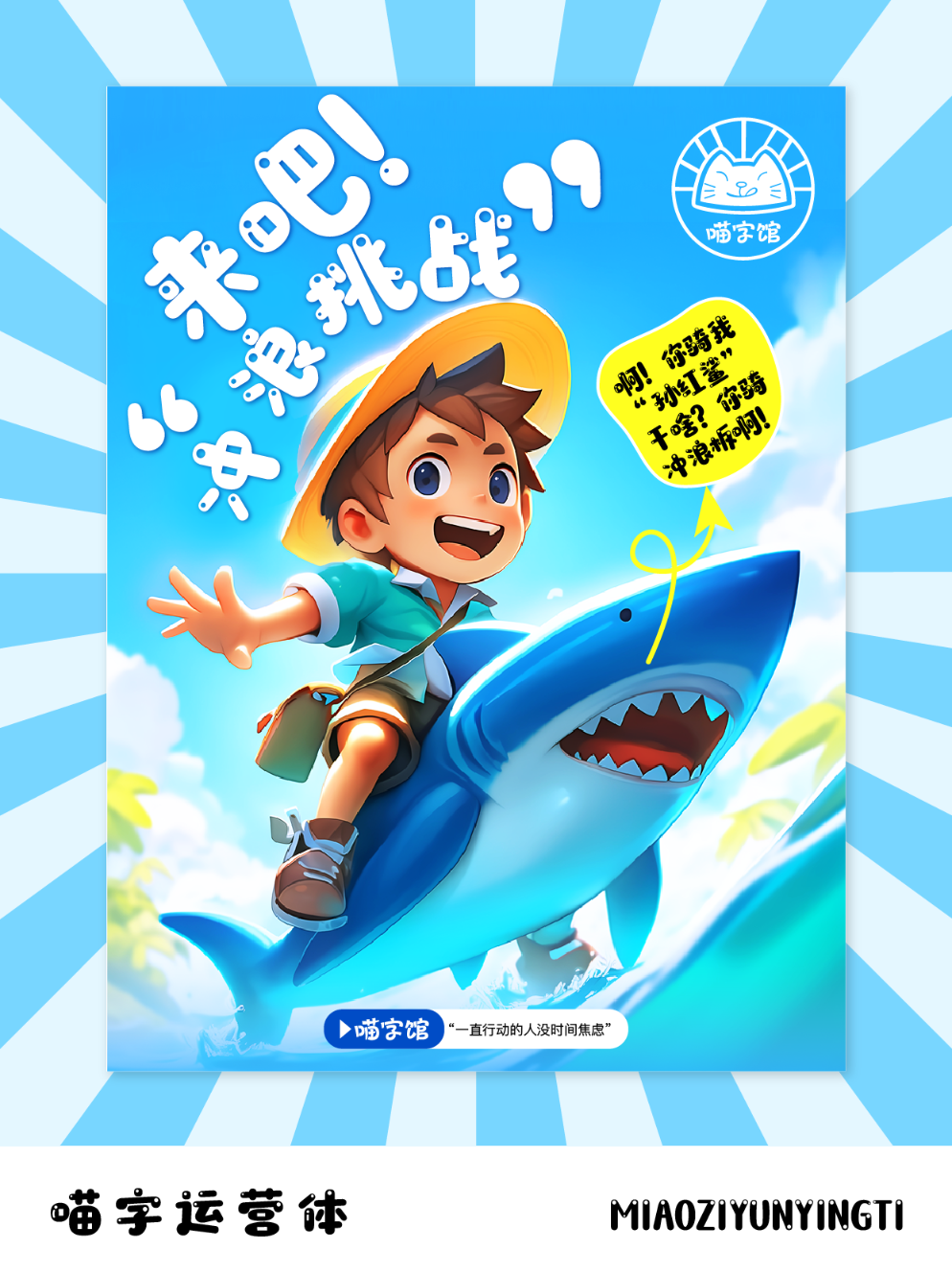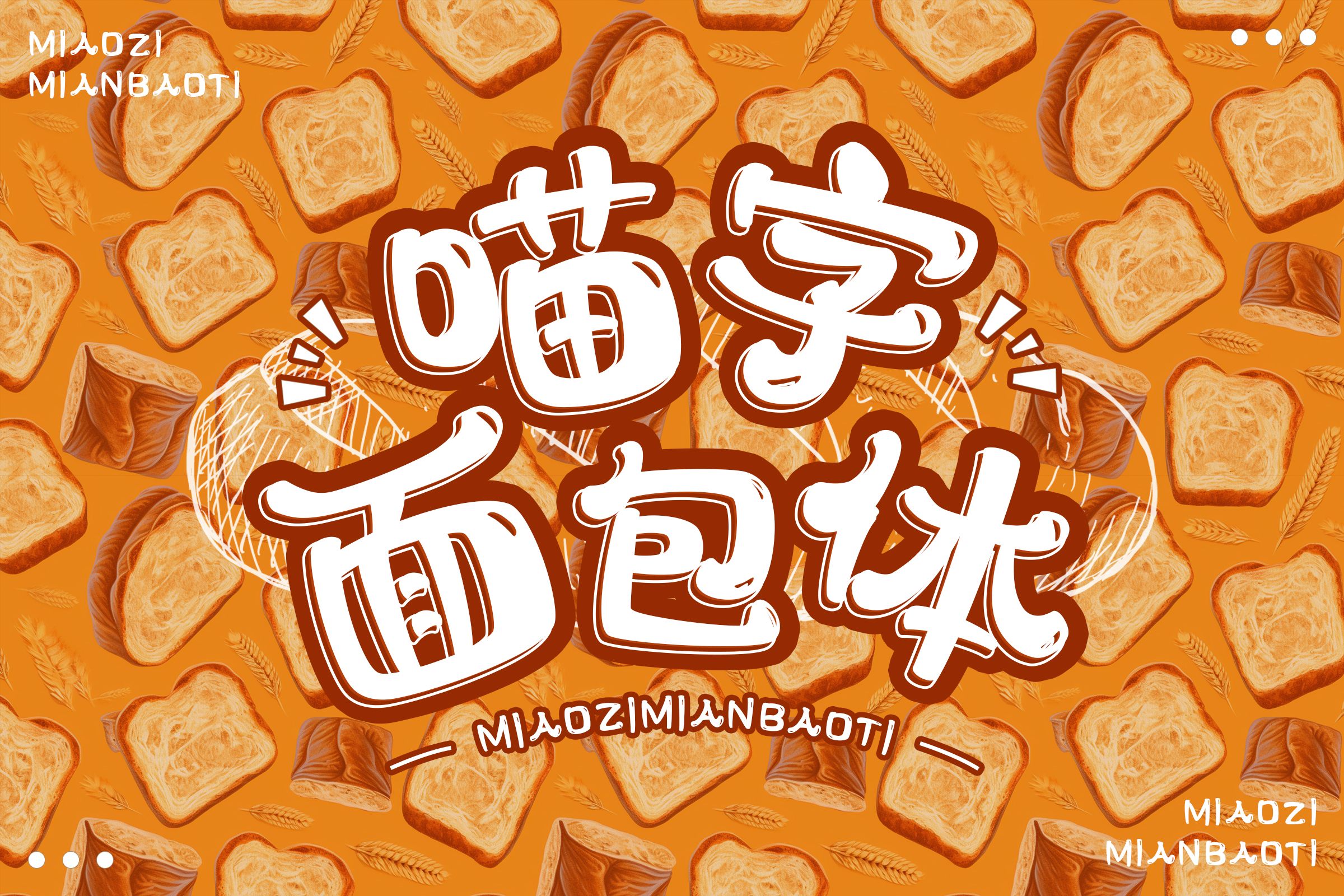
4款字体让你的甜品店设计甜度超标!
在甜品店的设计中,字体选择至关重要。它不仅能传递出店铺的风格和氛围,还能吸引顾客的注意力,提升品牌形象。今天,就为大家推荐四款专为甜品店设计量身打造的喵字系列字体。
1.喵字运营体
这款字体风格圆润,添加了小圆形的高光装饰,看起来非常可爱。它非常适合用于甜品店的菜单设计中,不仅易读性高,而且醒目,能让顾客一眼就看懂菜品信息。同时,喵字运营体的可爱风格也能为甜品店增添一份温馨和亲切感。
2.喵字海报体
这款字体整体错落有致,讲究灵活多变,非常适合运用于年轻化的品牌宣传海报上。甜品店可以利用喵字海报体设计各种促销活动海报,吸引年轻人的目光。它的实验风格排版也能让海报看起来更加独特和有趣,提升店铺的知名度和吸引力。
3.喵字面包体
则是一款定位于食品包装的细分字库产品。它的整体风貌轻盈圆润,手写感较强,每个字都有高光来凸显立体感和卡通感的设计特点。这种字体非常适合用在甜品店的食品包装产品中,如蛋糕盒、面包袋等。喵字面包体的可爱和卡通风格不仅能吸引顾客的注意力,还能让顾客在品尝美食的同时,感受到一份童趣和欢乐。
4.喵字文案体
这款字体巧妙融合了传统书法的韵律与现代设计的简洁,每一笔一划都透露着知性之美。它特别适合用于甜品店的文案设计中,如店铺介绍、产品描述等。喵字文案体的阅读流畅性和视觉舒适度能让顾客更加愉悦地浏览店铺信息,提升购物体验。
总之,这四款喵字系列字体各有特色,都能为甜品店的设计增添一份独特的魅力。无论是菜单设计、海报制作还是食品包装,都能找到适合的字体来展现店铺的风格和氛围。希望这些推荐能帮助甜品店打造出更加吸引人和专业的品牌形象。